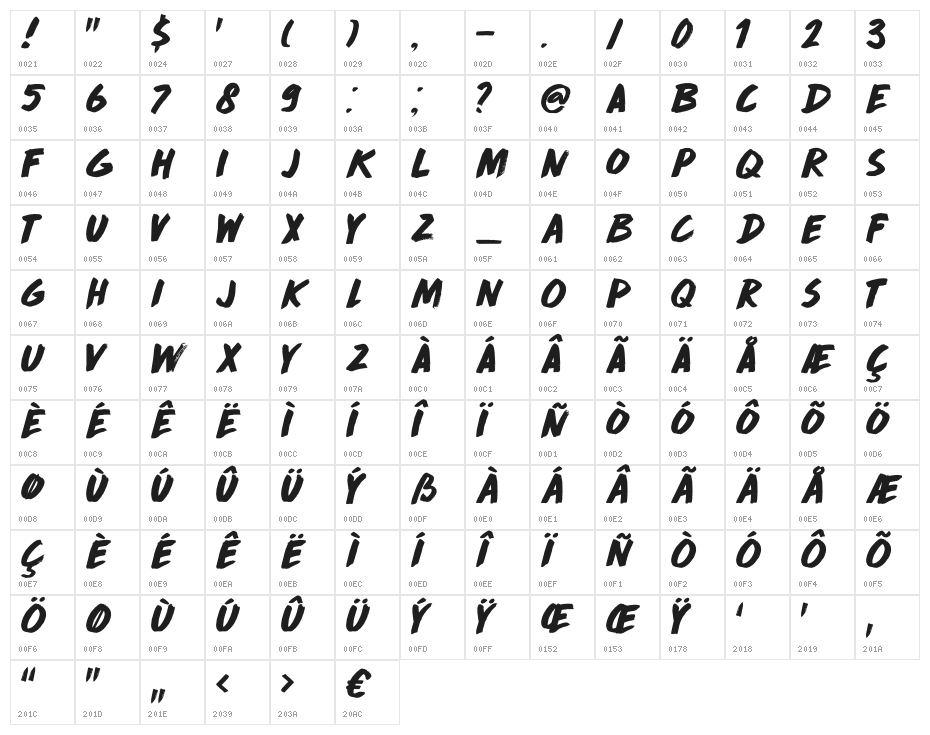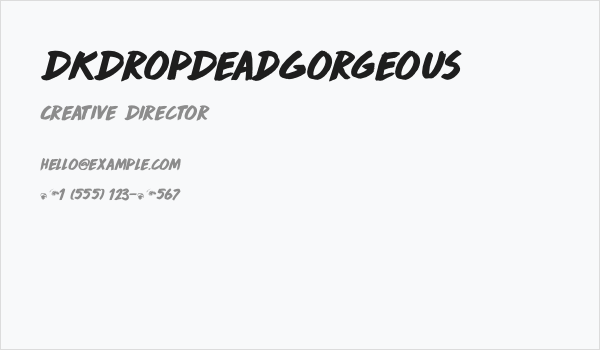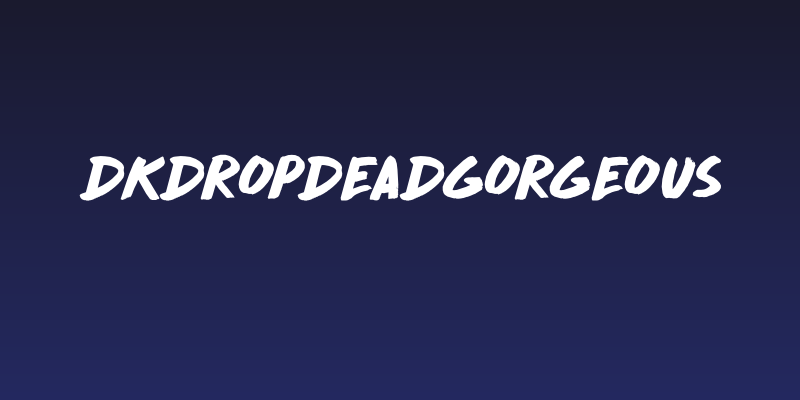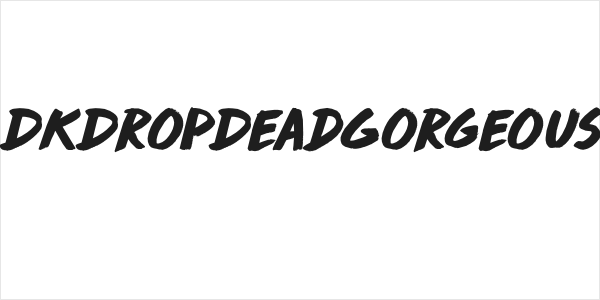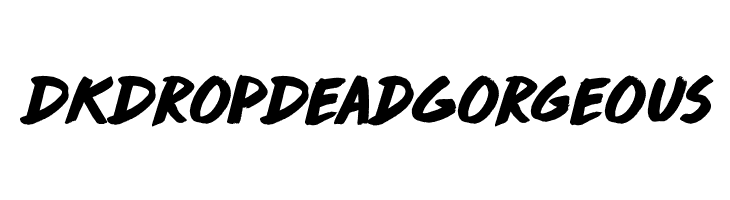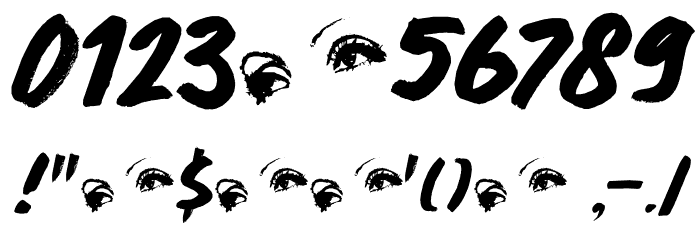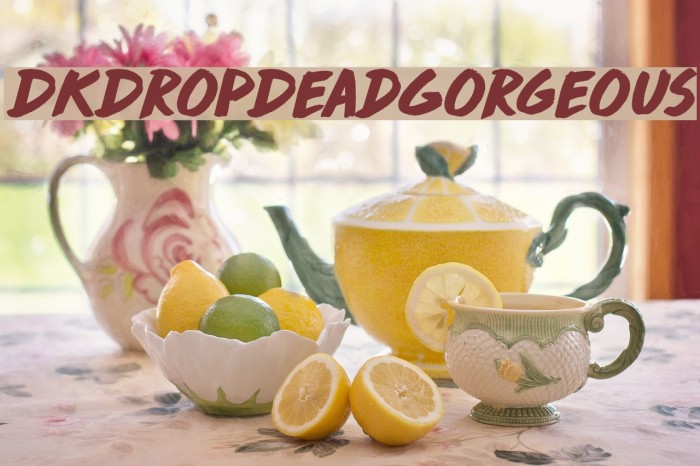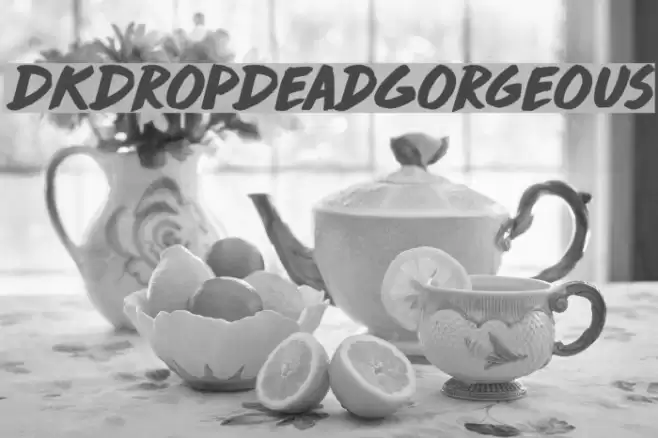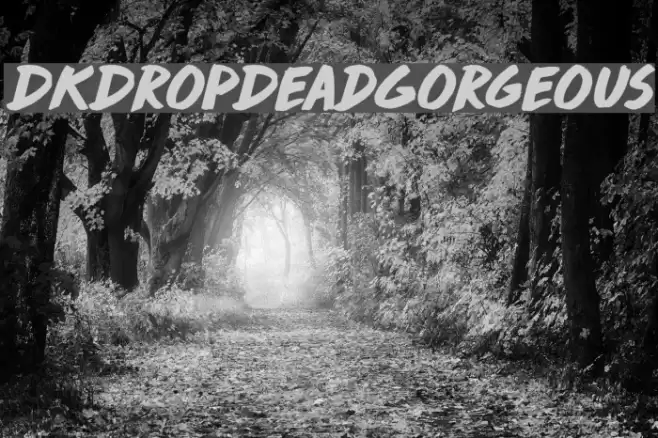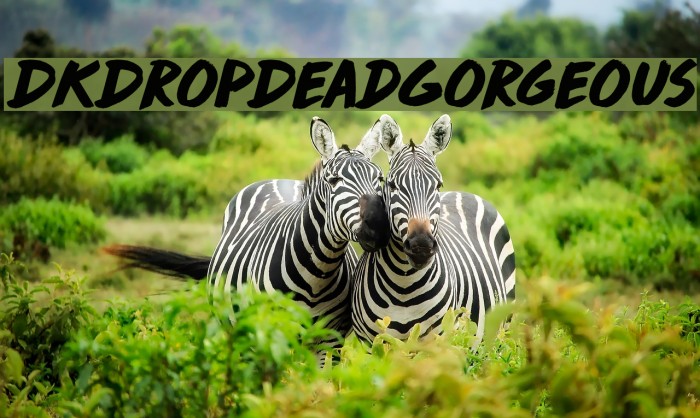
DKDropDeadGorgeous Font
✎ Messy
| Общий стиль | Modern, Artistic |
| Рекомендуемые проекты | Ideal for creative projects such as posters, album covers, and branding materials that require a bold, artistic touch. |